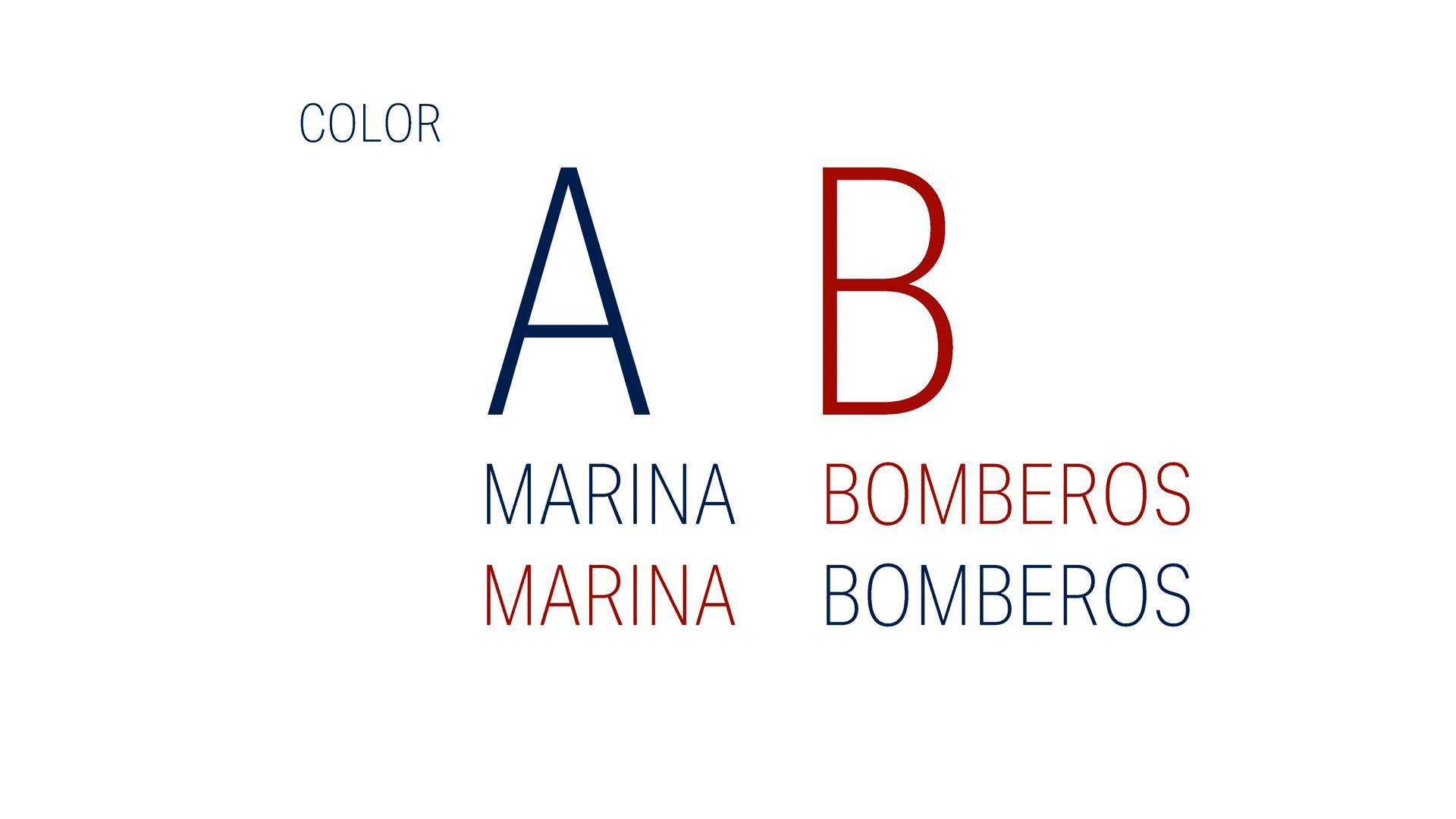
Conception d’affiches typographiques expérimentales
Attributs expressifs de la typographie
À propos de la leçon : Attributs expressifs de la typographie
“Ici, nous nous concentrerons sur la connaissance des attributs expressifs de la lettre, tels que: la forme, la couleur, la taille, le poids et la position, entre autres. ”
Dans cette leçon, BlueTypo aborde le sujet : Attributs expressifs de la typographie, qui fait partie du cours Domestika en ligne : Conception d’affiches typographiques expérimentales. Exprimez un concept créatif en mêlant les techniques numériques et traditionnelles.
“Maintenant que vous avez vu comment fonctionnent les attributs formels pour sélectionner une police, nous approfondirons les attributs expressifs de la typographie afin que vous puissiez voir comment un concept se matérialise à travers ces attributs. Voyons la structure, la forme, poids, couleur, position, entre autres éléments, voyons voir. Dans les attributs expressifs, il y a des aspects tels que la structure de la lettre, forme, couleur, taille des caractères, le poids lié à l'épaisseur et à la position de la police dans le champ visuel. La structure de la lettre fait référence à la con...”